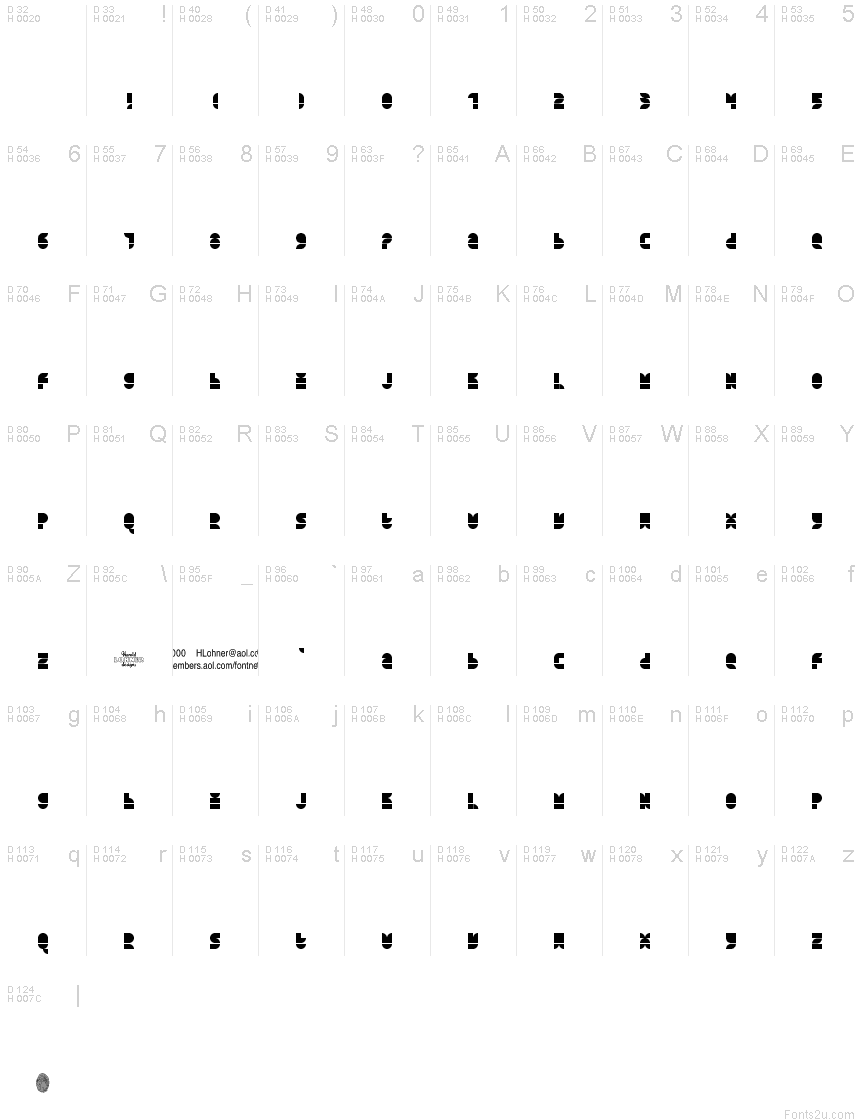
Quarterround Tile di Harold Lohner è un font display gratuito dal carattere groovy, con una spiccata estetica modulare che richiama la fine degli anni '60 e l'inizio degli anni '70. Le lettere sono costruite utilizzando pesanti quarti di cerchio, blocchi e tagli netti, che conferiscono all'alfabeto un ritmo simile a una pavimentazione, dove angoli arrotondati e decise interruzioni verticali si ripetono costantemente.
È ideale per lettering su poster, packaging ispirati al mondo dei dischi, branding di caffè in stile retrò, titoli e brevi linee editoriali dove bastano poche grandi lettere per trasmettere lo stile giusto. Trattandosi di un font gratuito, è perfetto anche per monogrammi e capilettera, poiché le forme ampie e arrotondate creano silhouette d'impatto anche in contesti molto brevi.